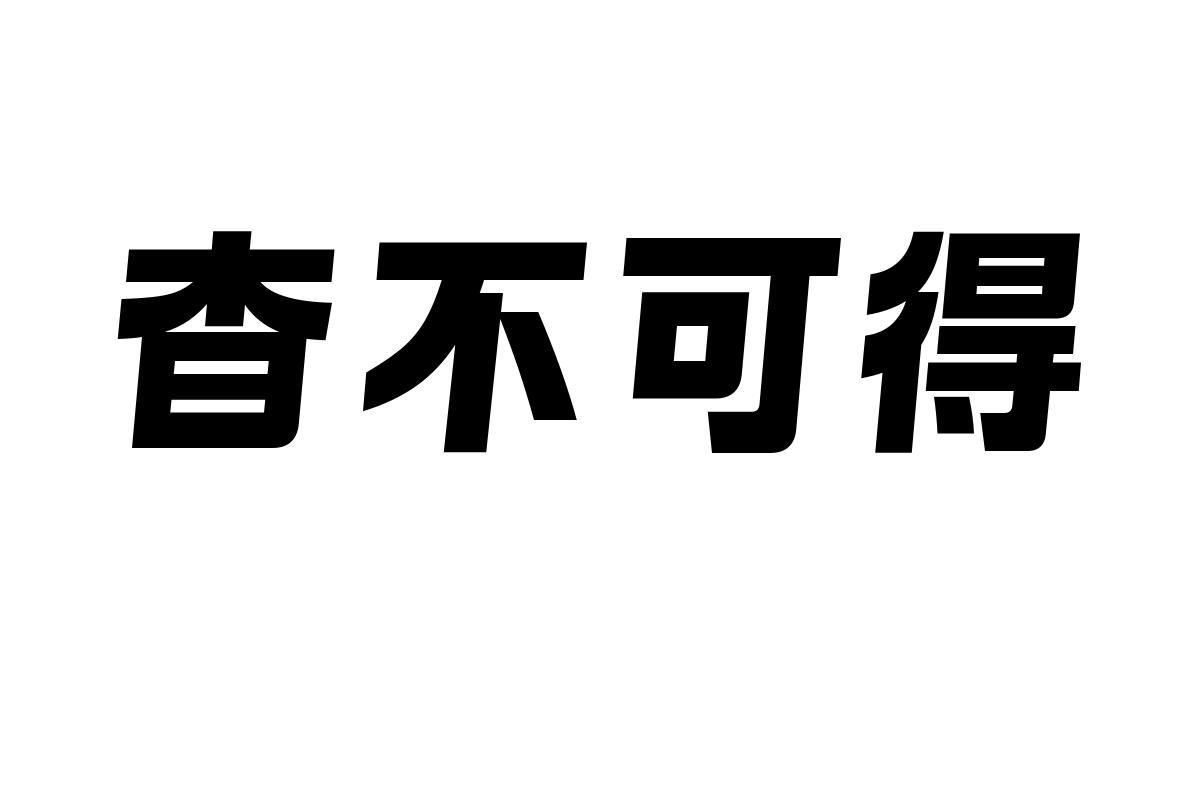
“也字工厂”是一款免费的中文字体,由上海“也字”文化创意有限公司开发。这款字体以其独特的设计而受到许多设计师和用户的喜爱。它的字形结构独特,笔画流畅,给人一种优雅、大方的感觉。同时,也字工厂熬夜黑的字体还具有良好的可读性和易用性,适合用于各种印刷品和电子媒体。
该字体具有以下特点:
1. 字体大小:也字工厂熬夜黑支持多种字体大小,从小到大均可轻松调整,满足不同场景的需求。
2. 字体风格:这款字体线条流畅,字形优美,给人一种优雅、大方的感觉。同时,它还具有一定的艺术感,适合用于需要突出文字美感的场合。
3. 适用范围:也字工厂熬夜黑适用于各种印刷品和电子媒体,如报纸、杂志、书籍、海报、广告、网页等。此外,它还可以应用于各类办公软件,如Word、Excel、PPT等。
总的来说,也字工厂熬夜黑是一款功能强大、适用范围广的免费中文字体,深受广大设计师和用户的喜爱。